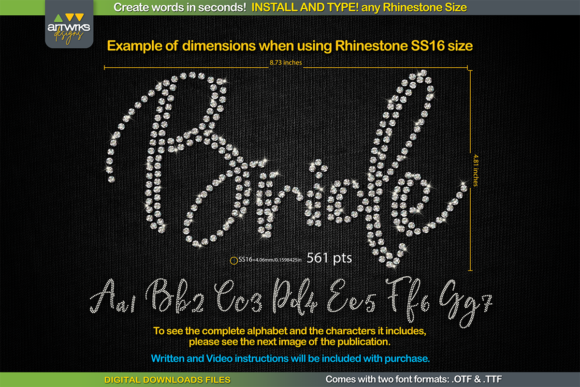
RS01 Cursiva Rhinestone Template TTF
Mencari elemen reka bentuk yang sesuai boleh menjadi mencabar, tetapi RS01 Cursiva Rhinestone Template TTF menawarkan koleksi luar biasa yang menaik taraf karya anda serta-merta.
Dicipta dengan ketepatan, RS01 Cursiva Rhinestone Template TTF menyediakan vektor yang bersih, tipografi yang licin dan lesen komersial untuk ketenangan fikiran.
Sama ada anda mencipta produk POD (Print on Demand), jemputan perkahwinan atau grafik media sosial, RS01 Cursiva Rhinestone Template TTF amat bersesuaian.